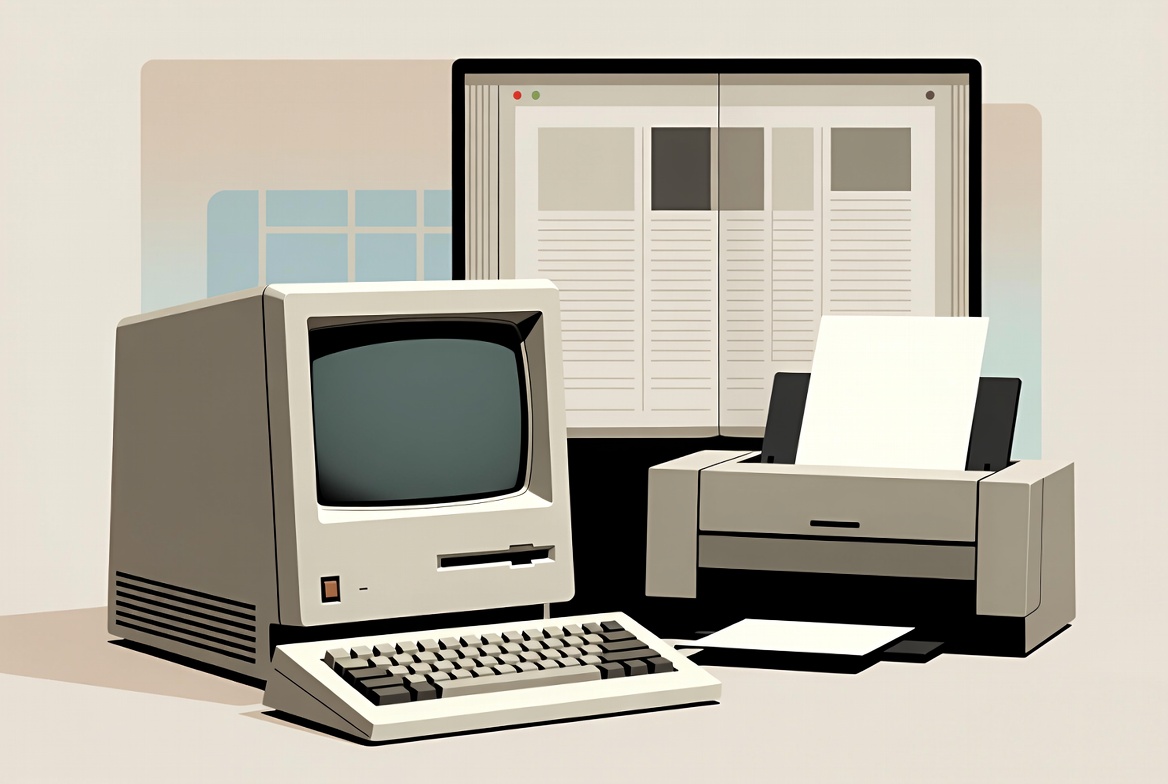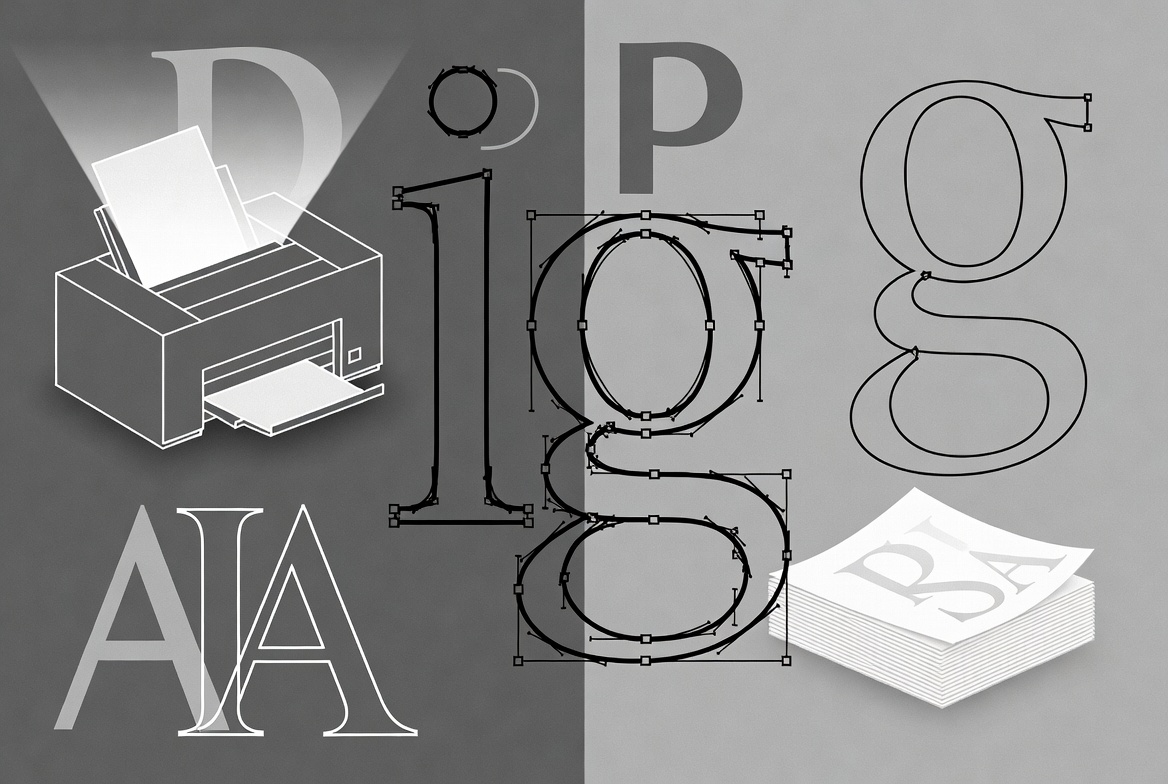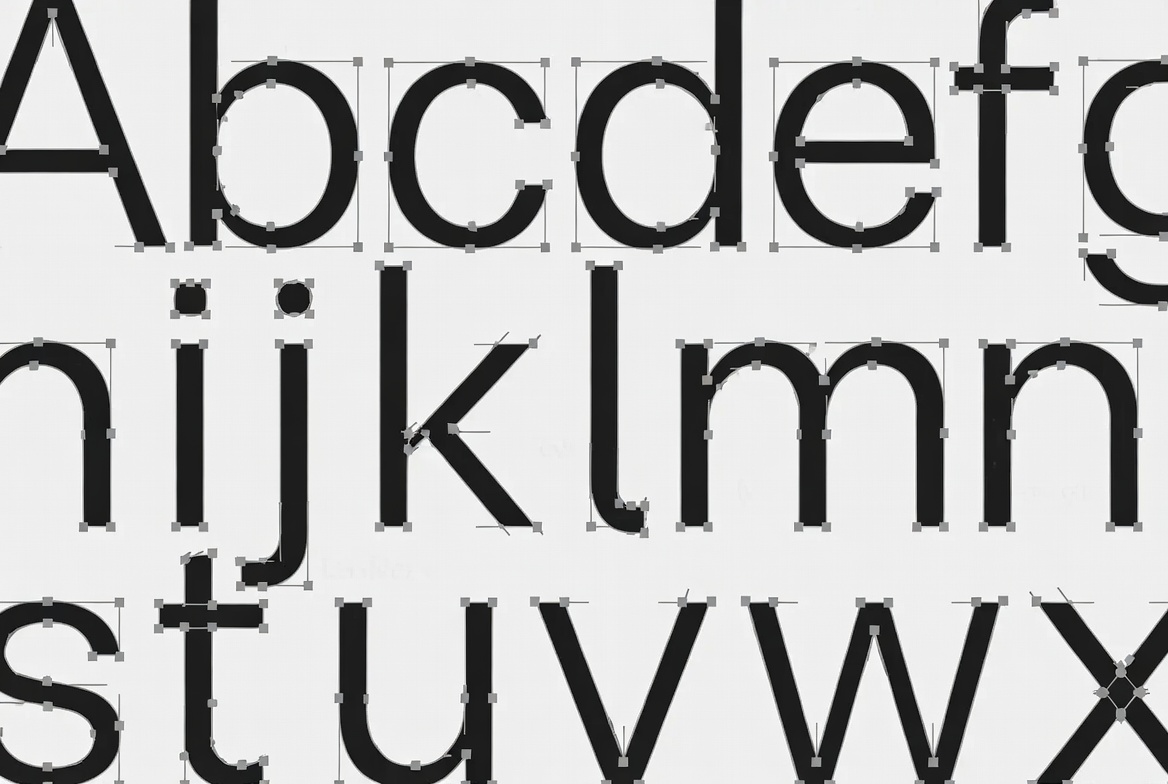
PostScript-Schriften – Die Technologie, die den digitalen Satz ermöglicht hat
Wie PostScript und Type-1-Schriften in den 1980er-Jahren den professionellen digitalen Satz und die Desktop-Publishing-Revolution möglich gemacht haben.
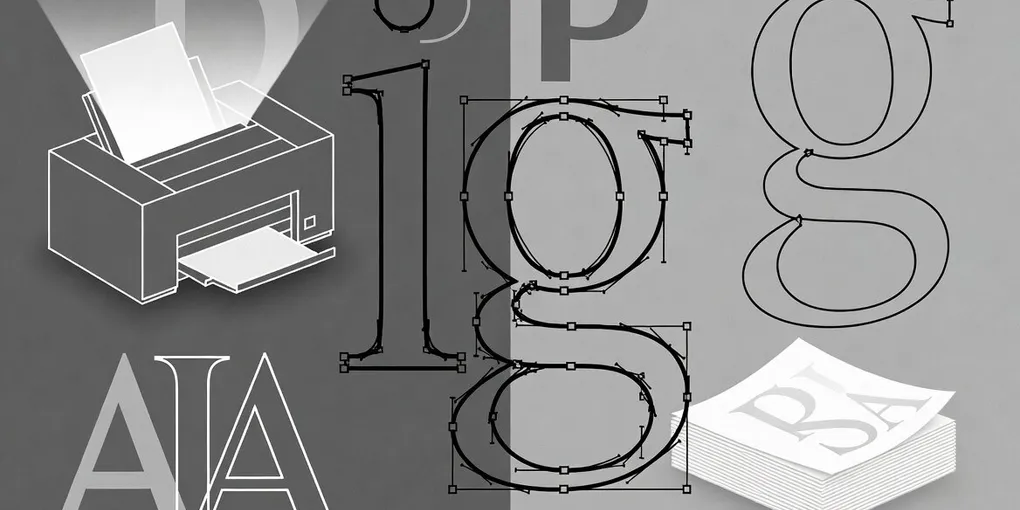
Bevor in den 1980er-Jahren PostScript und die dazugehörigen Schriften kamen, war professioneller Satz weitgehend an teure, spezialisierte Systeme gebunden. Schriften existierten oft als Bitmap-Versionen für feste Größen, und das, was man auf dem Bildschirm sah, entsprach selten dem späteren Druckbild.
PostScript und die Type-1-Schriften änderten das grundlegend. Sie legten den technischen Grundstein dafür, dass digital erstellte Layouts auflösungsunabhängig und in hoher Qualität ausgegeben werden konnten.
Illustration: Vektorielle Schriftformen, Ausgabegeräte und die Idee der auflösungsunabhängigen Darstellung
Was ist PostScript?
PostScript ist eine Seitenbeschreibungssprache, die Adobe 1984 vorstellte. Entwickelt wurde sie unter der Leitung von John Warnock und Chuck Geschke. Im Unterschied zu einfachen Druckeranweisungen beschreibt PostScript eine ganze Seite als Programm: Texte, Grafiken und Bilder werden als mathematische Objekte definiert.
Der entscheidende Vorteil: Dieselbe Beschreibung kann auf Geräten mit sehr unterschiedlicher Auflösung ausgegeben werden – vom 300-dpi-Laserdrucker bis zum hochauflösenden Imagesetter. Die Seite bleibt dabei in ihrer Struktur und Proportion gleich.
Type-1-Schriften: Outlines statt Bitmaps
Zusammen mit PostScript entwickelte Adobe ein neues Schriftformat: die Type-1-Schriften (auch PostScript Type 1, PS1 oder T1 genannt).
Illustration: Skalierbare Vektorumrisse und das Prinzip des Hintings
Statt fester Pixelbilder beschreiben Type-1-Schriften die Buchstabenformen als vektorielle Umrisse (Outlines). Die Kurven basieren auf kubischen Bézier-Kurven. Dadurch lassen sich die Zeichen auf jede beliebige Größe skalieren, ohne an Schärfe zu verlieren.
Wichtige Eigenschaften
- Auflösungsunabhängigkeit: Die Schrift wird erst beim Ausgeben in die Auflösung des Zielgeräts umgerechnet.
- Hinting: Zusätzliche Informationen steuern, wie Stämme, Bögen und Überhänge bei kleinen Größen oder niedriger Auflösung an das Pixelraster angepasst werden.
- Kompakte Kodierung: Type 1 verwendet einen eingeschränkten, optimierten Ausschnitt der PostScript-Sprache.
Damit war es erstmals praktikabel, eine Schrift einmal zu digitalisieren und sie zuverlässig in ganz unterschiedlichen Größen und auf verschiedenen Ausgabegeräten einzusetzen.
Type 1 und Type 3
Adobe unterschied früh zwischen verschiedenen Font-Typen:
| Typ | Merkmale | Hinweis |
|---|---|---|
| Type 1 | Eingeschränkter PostScript-Umfang, standardisiertes Hinting, optimiert | Das professionelle Standardformat |
| Type 3 | Voller PostScript-Sprachumfang, flexibler, aber ohne standardisiertes Hinting | Eher für spezielle oder experimentelle Zwecke |
Type 1 setzte sich als das Format für den professionellen Einsatz durch. Die Spezifikation wurde von Adobe zunächst zurückgehalten und erst 1990 veröffentlicht. Bis dahin blieben hochwertige Type-1-Schriften eng an Adobes eigene Technologie und Lizenzpolitik gebunden.
Die Desktop-Publishing-Revolution
PostScript-Schriften entfalteten ihre volle Wirkung erst im Zusammenspiel mit weiteren Komponenten:
- dem Apple Macintosh mit grafischer Oberfläche
- dem Apple LaserWriter (1985), der einen PostScript-Interpreter und eingebaute Type-1-Schriften mitbrachte
- Aldus PageMaker, dem ersten weit verbreiteten Layoutprogramm, das PostScript ansteuern konnte
Diese Kombination ermöglichte zum ersten Mal in größerem Maßstab das Prinzip WYSIWYG (What You See Is What You Get): Das Layout auf dem Bildschirm entsprach weitgehend dem späteren Druck. Professionelle Typografie war damit nicht mehr ausschließlich den klassischen Satzbetrieben vorbehalten.
Illustration: Die Kombination aus Computer, Laserdrucker und Layoutsoftware
In den LaserWriter-Geräten waren von Anfang an Kernschriften wie Times und Helvetica enthalten. Adobe baute parallel die Adobe Type Library auf und lizenzierte zahlreiche klassische und neue Schriften für das neue Format.
Technische Realität im Alltag
In der Praxis bestanden Type-1-Schriften oft aus mehreren Dateien: einer Datei mit den Outline-Daten und einer mit den Metriken (Laufweiten, Kerning). Auf dem Macintosh kamen zusätzlich bitmap-basierte Screen-Fonts hinzu, bis Programme wie Adobe Type Manager (ATM) die Bildschirmdarstellung der Outlines verbesserten.
Trotz dieser Komplexität dominierten PostScript Type-1-Schriften über zwei Jahrzehnte den professionellen Publishing-Bereich – von der Zeitschriftengestaltung bis zur hochwertigen Buchproduktion.
Vom Alleinstellungsmerkmal zum Erbe
Ab den frühen 1990er-Jahren entstand mit TrueType (Apple und Microsoft) eine Konkurrenztechnologie. Später einigten sich die großen Hersteller auf OpenType, ein Format, das sowohl PostScript-Outlines (CFF) als auch TrueType-Outlines aufnehmen kann und deutlich erweiterte typografische Möglichkeiten bietet.
Ihr direkter Nachfolger ist OpenType. Die historischen und praktischen Folgen des schrittweisen Rückzugs der Type-1-Unterstützung – besonders für ältere, teuer erworbene Schriftbibliotheken – sind ein eigenes Thema und Gegenstand des nächsten Artikels.